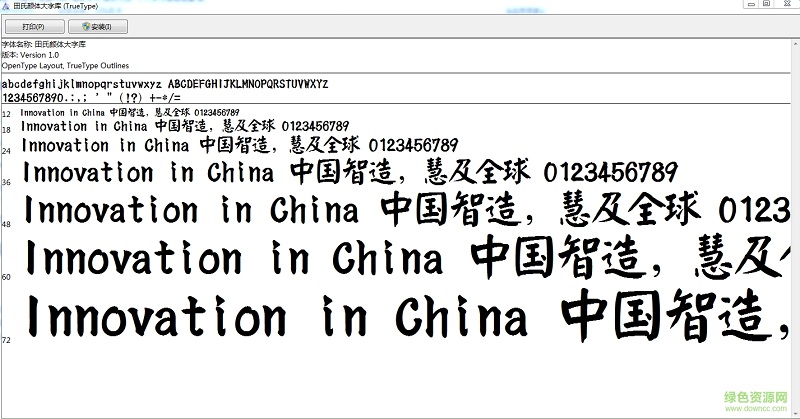
田氏顏真卿字體是一款根據(jù)唐代著名書法家顏真卿的書法整合修正的字體,這款字體精妙端莊,遒勁有力,極具風(fēng)骨,需要的朋友快來綠色資源網(wǎng)下載吧!
顏真卿書法精妙,擅長行、楷,創(chuàng)“顏體”楷書,與趙孟頫、柳公權(quán)、歐陽詢并稱為“楷書四大家”。又與柳公權(quán)并稱“顏柳”,被稱為“顏筋柳骨”。